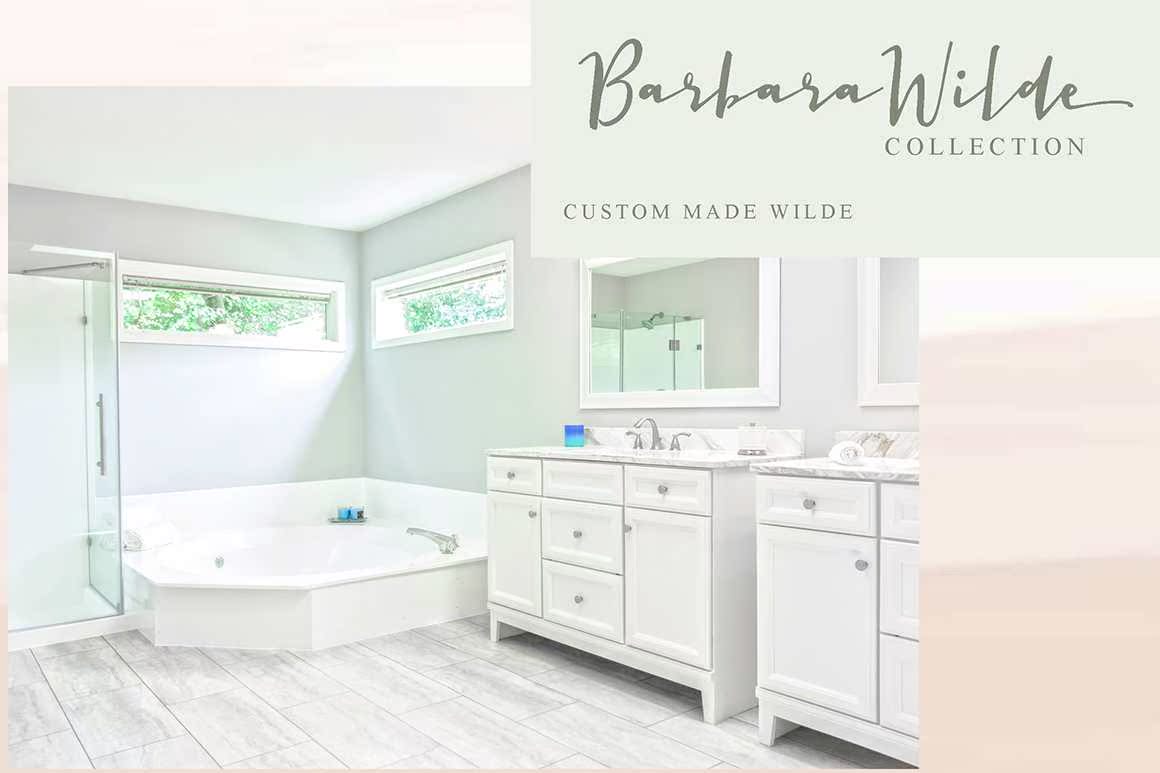
该签名器是一款有机手写字体,适用于品牌推广、签名、婚礼宣传、促销、产品包装和其他需要。该字体现代、简单,但仍然真实。您将获得全套大小写字母、数字和标点符号、多语言符号、,Ligature and Ternate Slower签名器是一款适用于品牌推广、签名、婚礼宣传、促销、产品包装和其他需要的有机手写字体。这款字体现代、简单,但仍然真实。您将获得全套大小写字母、数字和标点符号、多语言符号、Ligature and Ternate Slower签名器